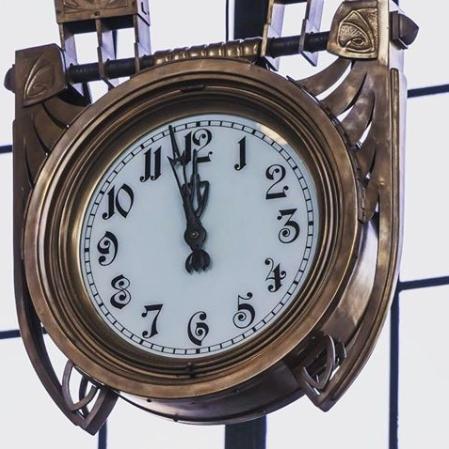
Suche den Font aus dieser Fabrikuhr, wahrscheinlich Deutschland 1900-1920
Leider kann ich sehr wenig Informationen beitragen. Das Foto erhielt ich von einem Bekannten, der aber nicht mehr sagen konnte, wo er es her hat.
Aufgrund der Uhrengestaltung, der Zeiger und des verwendeten Fonts vermute ich eine Entstehung etwa um 1900 bis 1920.
Ich suche genau diesen Font, schaue aber gerne auch Alternativen an. Bin auch gerne bereit, dafür zu zahlen.
Zumindest ähnlich, auf die Schnelle:
"Jugendstil" wäre ein gutes Stichwort für die Suche.
Hermann, das wird wahrscheinlich so sein, dass es damals keinen entsprechenden Font gab. Aber vielleicht heute...
Bertel, danke für die Links. Dort gibt es auch ein viel besseres Bild der Uhr.
-Im Grunde muss man fast sagen, dass nahezu alles, was bis in die späten 1960er Jahre hinein nicht im Buchdruck gedeuckt wurde so gut wie nie ´nacgh einer als Bleilettern gelieferten Schrift geastaltet wurde. Selbst einfache Texte in Groteskschrift wurden damals von mehr oder weniger begabten Handwerkern frei gezeichnet. Hierbei hat man sich erher an Fachbücher, die in die Gestaltung von Schridften einführten gehalten, als an Satzschriften.
Tja, schaut also nicht so gut aus. Jetzt habe ich mir diesen Font nun mal eingebildet. Die verspielten Zahlen passen einfach so gut zur Uhr und ich möchte dieses Ziffernblatt in eine Uhr einbauen lassen. Es handelt sich um ein Dioramenprojekt.
Daher wollte ich fragen -und hoffe, damit nicht gegen eine Forumsregel zu verstoßen- ob einer von euch Fonts entwirft und bereit wäre oder Interesse hätte, mir die Buchstaben von 1 bis 9 und der 0 als Font zu gestalten. Natürlich gegen Bezahlung. Vielen Dank.